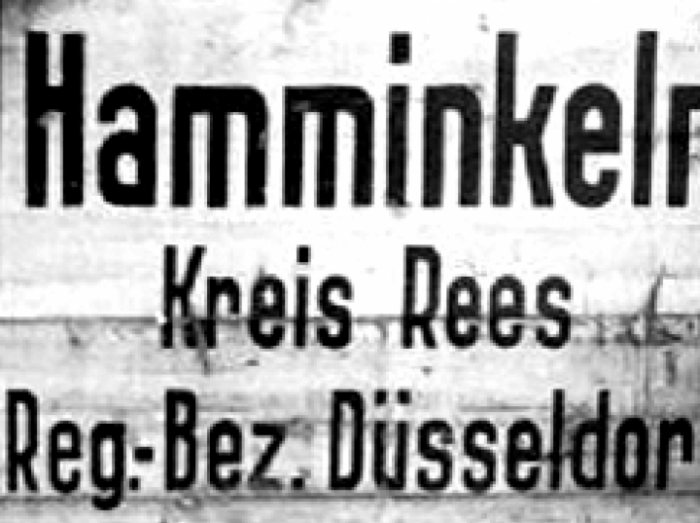
Und noch eine Schriftsuche
Es handelt sich hier, wie man sehen kann, um ein Ortseingangsschild aus vermutlich den 20er Jahren.
Vor allem das "k" und "R" macht mir Kopfzerbrechen.
Das ist damals vom örtlichen Schildermaler selbst gehäkelt, Es war ja die Zeit, in der sich die DIN 1451 gerade erst durchzusetzen begann, Gerade im Ländlicheren Raum wurde da viel selber gestrickte Schriften verwendet, von denen viele (noch) nicht digitalisiert wurden.
Allerdings suche ich eben auch solche Schriten, werde mir das Bild also speichern, und über Kurz oder etwas länger daraus einen Font häkeln. Im Moment ists zeitlich aber schlecht. Hast Du noch mehr davon, ruhig her damit!